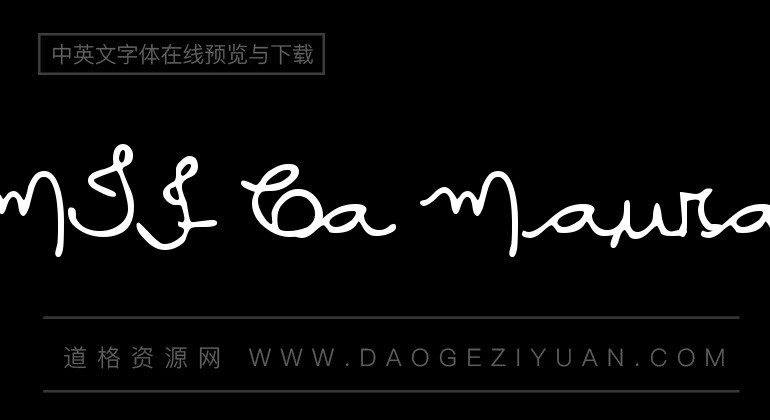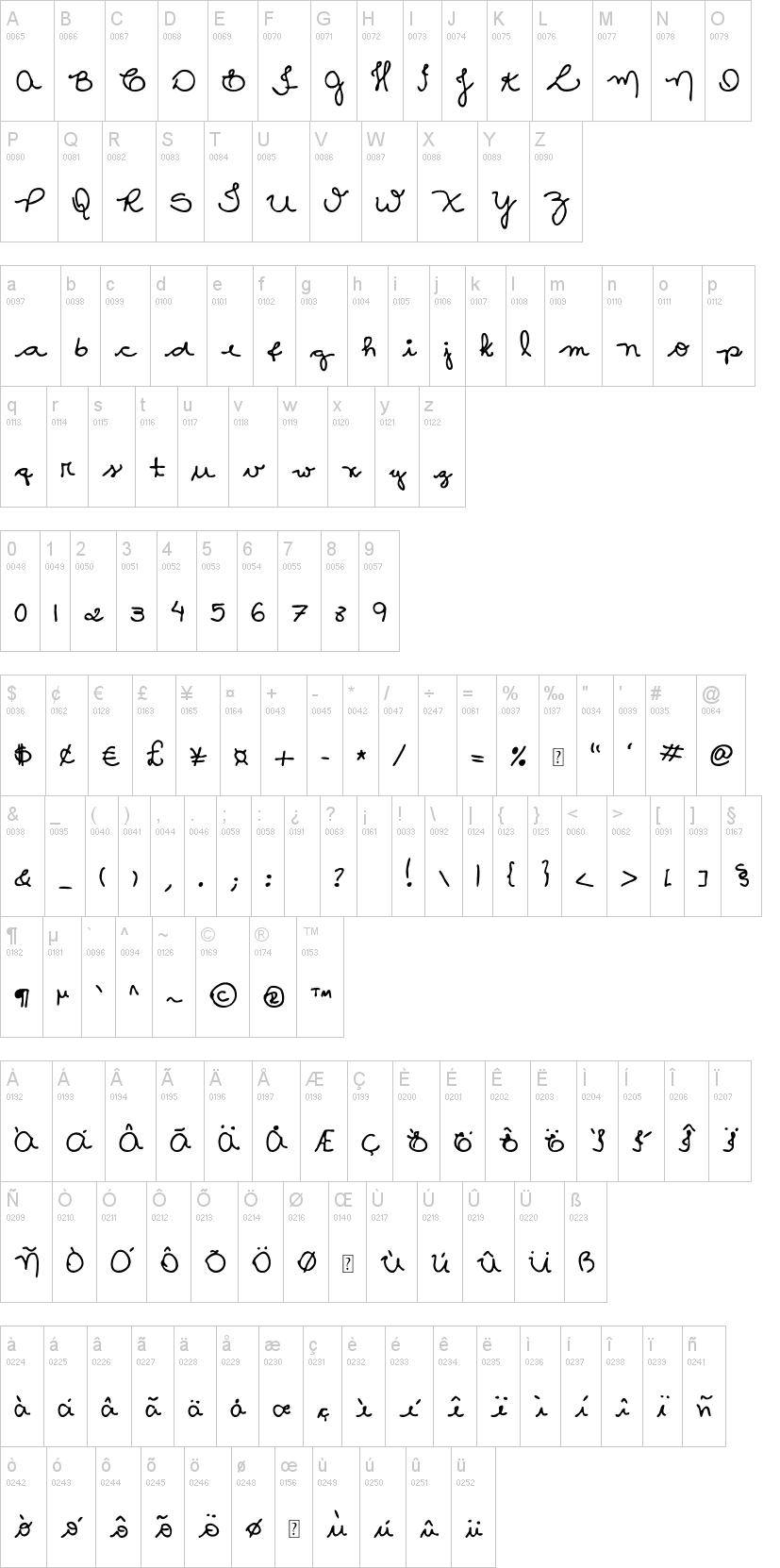
? MTF Ca Maura 是一款新的字体,由MTF设计师Maura McEvoy设计。它是一种现代的字体,拥有独特的外观和设计,可以用于创建现代、简洁的文本和标题。它有两种字重,分别是正常和粗体,支持多种语言,可以很容易地改变字体大小和样式,给文本增添更多的灵活性和选择。它还支持多种格式,可以应用于网页、印刷和图形设计等多种领域。内容介绍
MTF Ca Maura是一款非常不错的手写艺术字体,具有很好的视觉感,适合于文化类的宣传设计、商业类品牌的广告和产品包装设计以及个性化文字排版等较多场景。